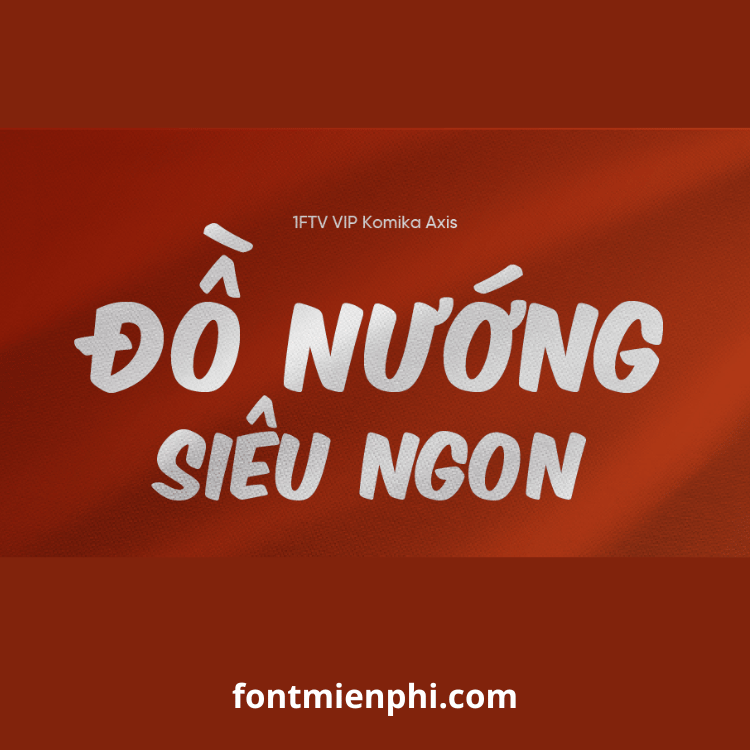
Font Việt hóa 1FTV VIP Komika Axis
Mô Tả Chi Tiết Font Việt Hóa “1FTV VIP Komika Axis”
1. Giới Thiệu Chung
1FTV VIP Komika Axis là một font chữ Việt hóa độc đáo, được thiết kế dựa trên phong cách comic (truyện tranh) và game, với nét chữ đậm, góc cạnh, mang đậm chất hoạt hình và năng động. Font này thích hợp cho các thiết kế game, poster, bìa sách, truyện tranh, logo, và các ấn phẩm sáng tạo cần sự bắt mắt.
2. Đặc Điểm Nổi Bật
✔ Phong cách Comic & Gaming: Nét chữ mạnh mẽ, góc cạnh, phù hợp với phong cách truyện tranh, game hoặc quảng cáo sôi động.
✔ Đa dạng ký tự: Hỗ trợ chữ hoa, chữ thường, số, ký tự đặc biệt và biểu tượng.
✔ Dễ đọc, dễ ứng dụng: Font có độ dày vừa phải, phù hợp cho cả tiêu đề và đoạn văn ngắn.
3. Ứng Dụng Phổ Biến
- Thiết kế game & esports (logo, giao diện, banner).
- Truyện tranh & hoạt hình (bìa truyện, speech bubble, tiêu đề).
- Poster quảng cáo, áp phích sự kiện.
- Thiết kế áo thun, sticker, merch.